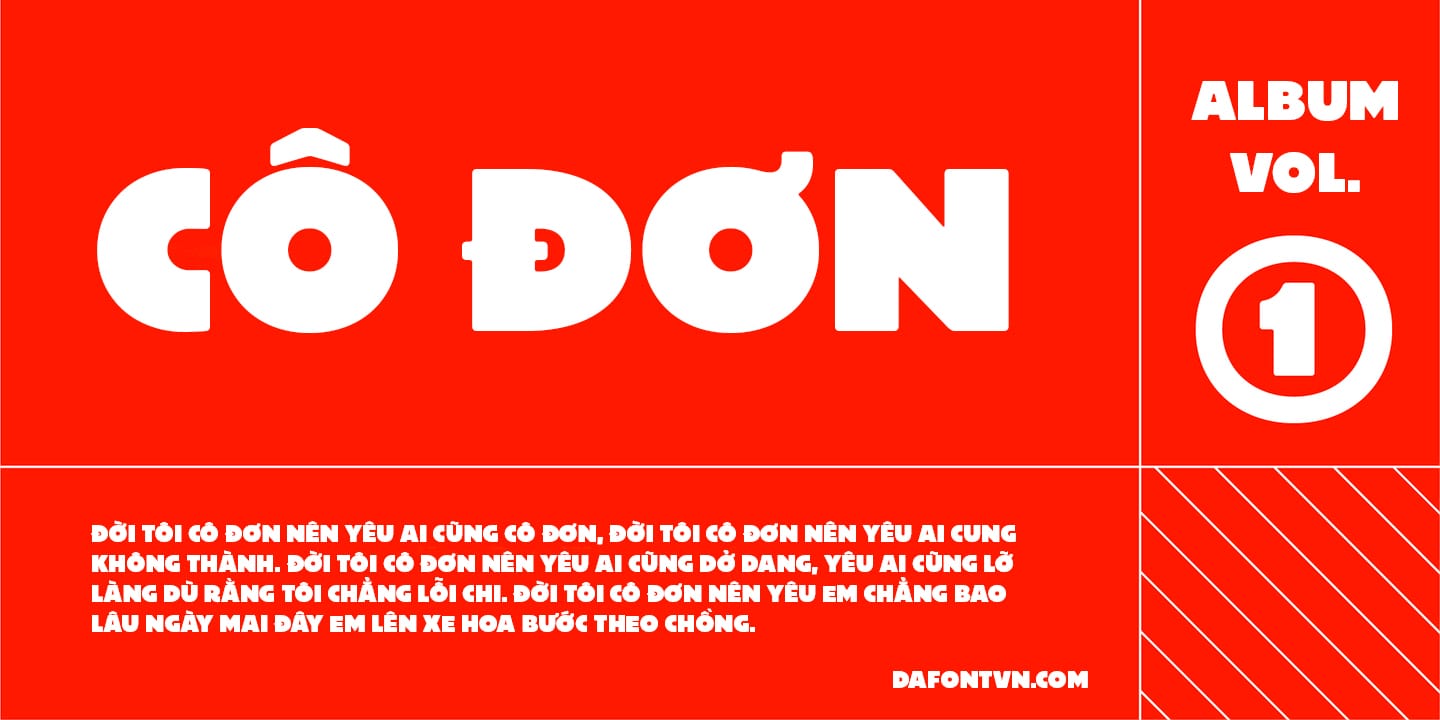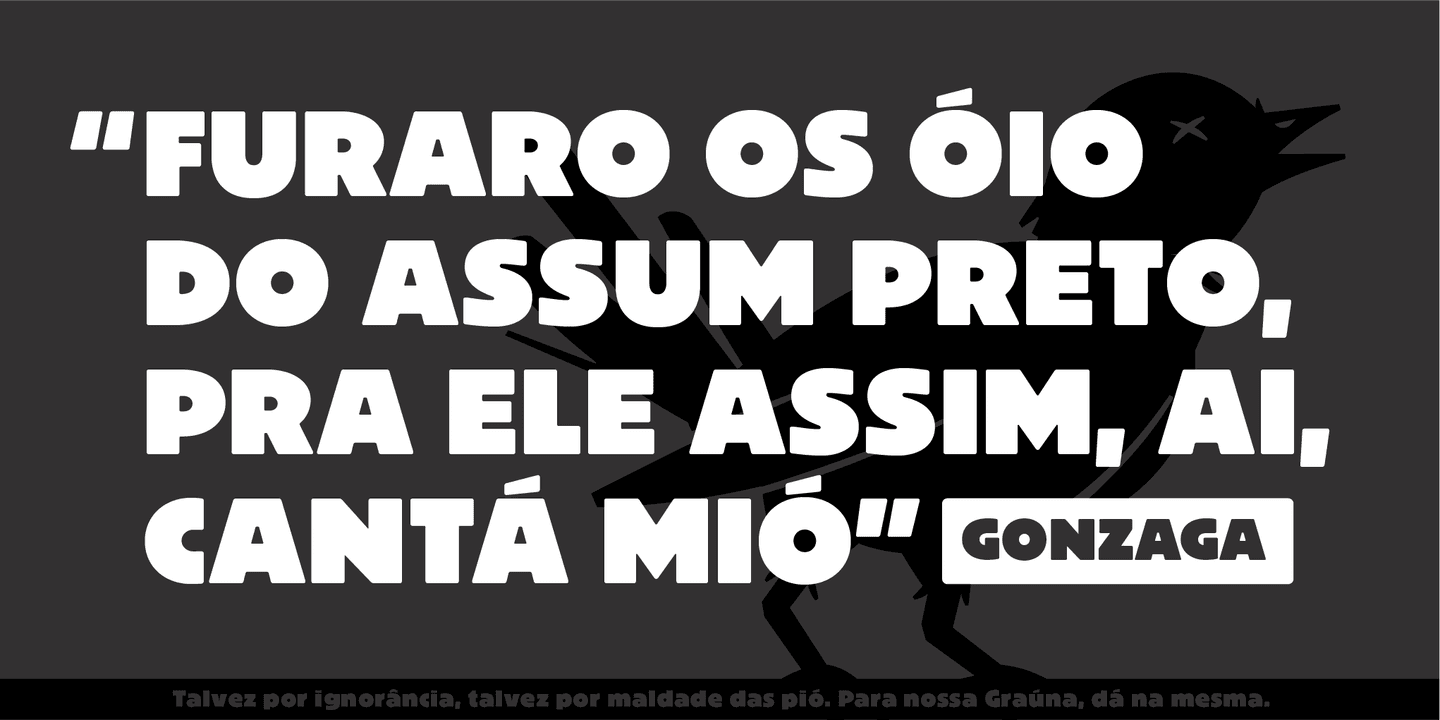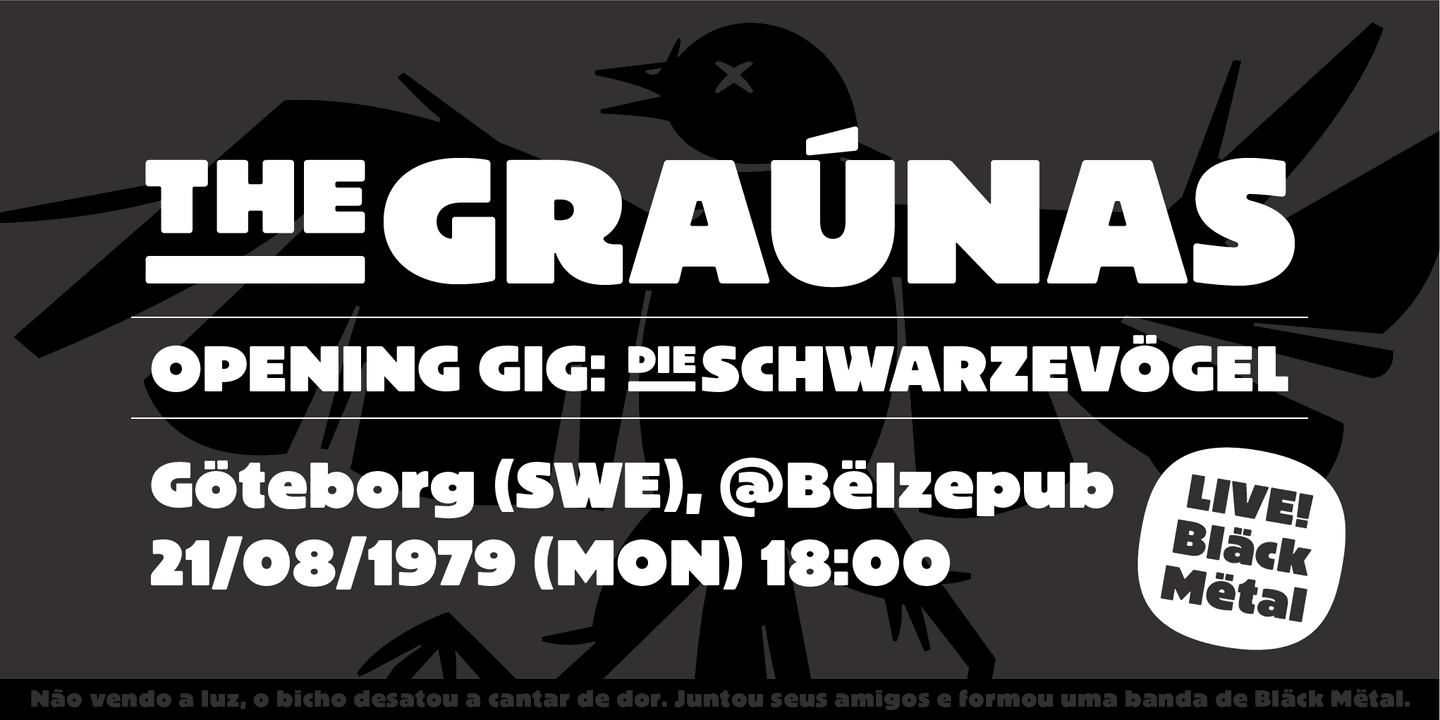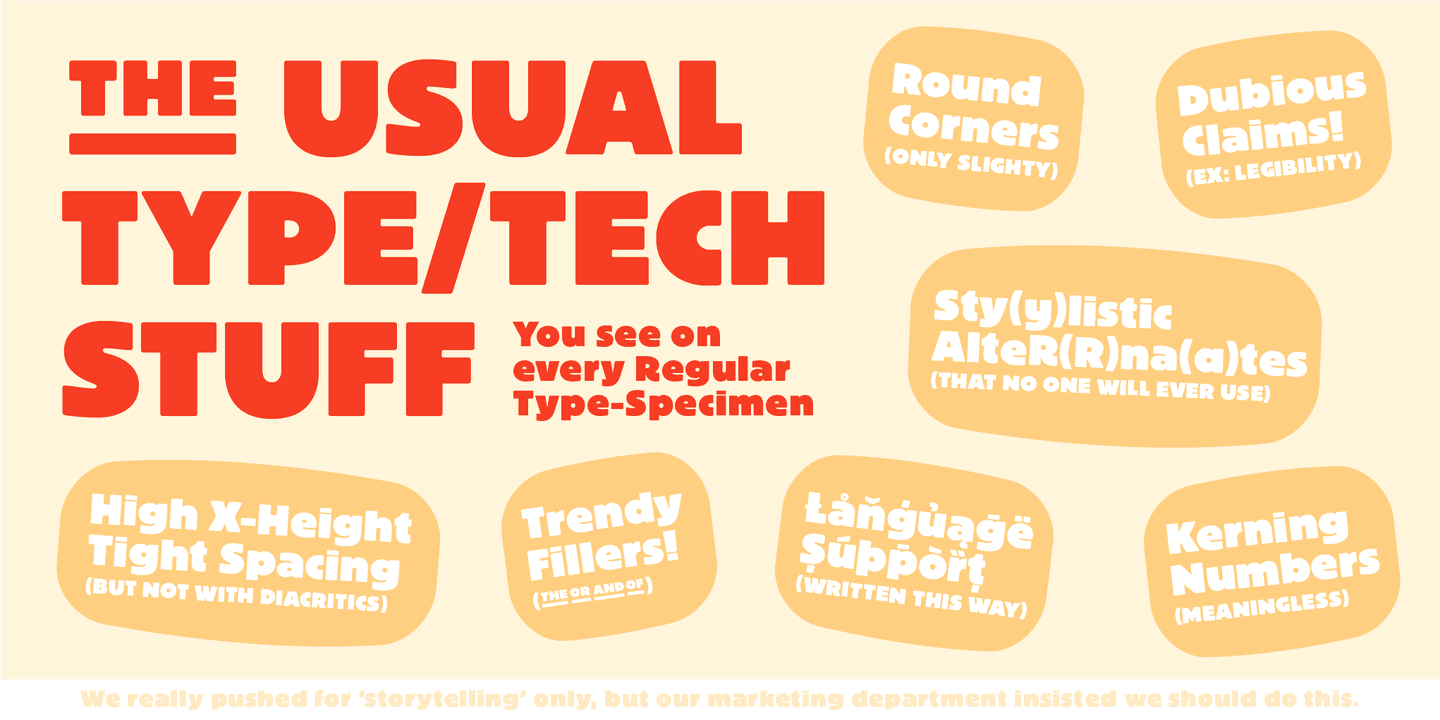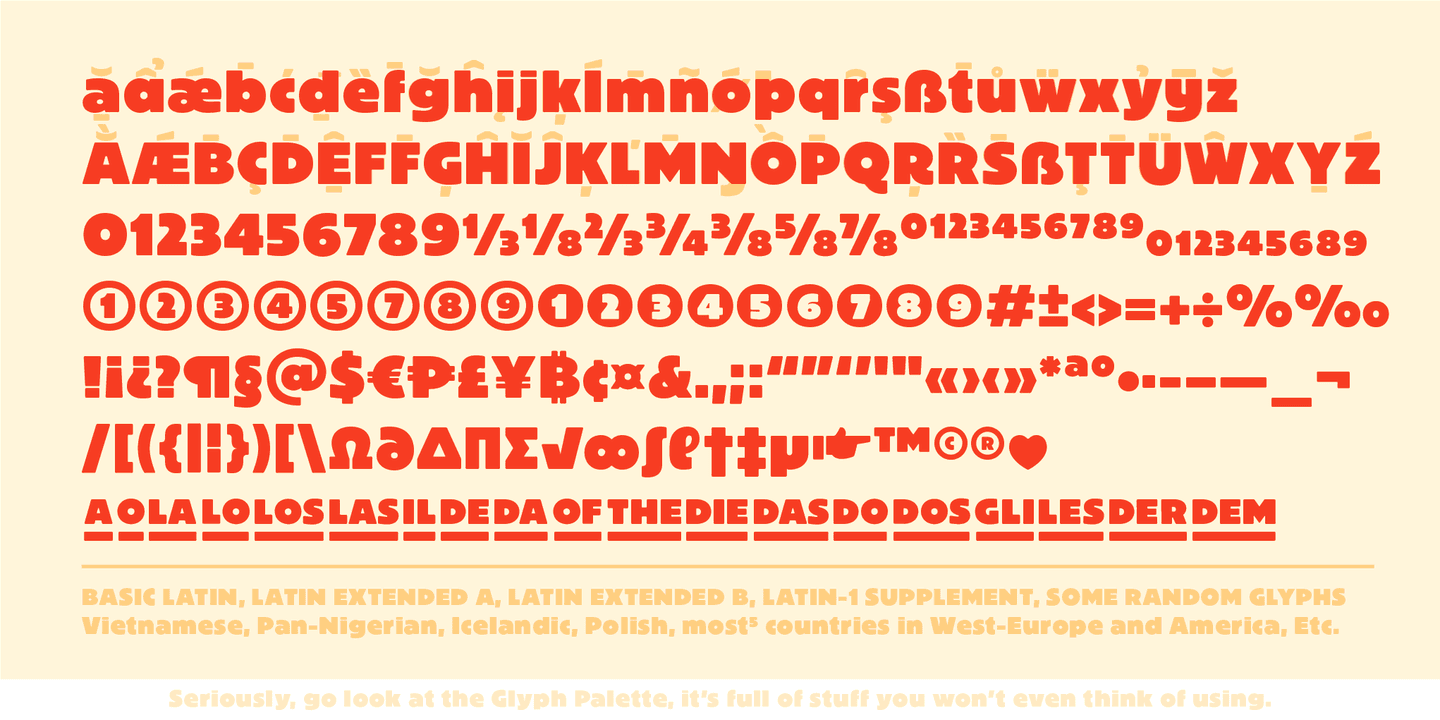
Font Grauna Việt Hóa – Font chữ to, đậm
Grauna Việt Hóa là ‘serious typeface’ đầu tiên của Typeóca. Đây là một font chữ phù hợp dành cho các thiết kế tiêu đề hoặc logo bởi các chữ cái được thiết kế với các nét đậm và to.Ý tưởng là tạo ra một bản phục hồi của Block Heavy, loại bỏ cấu trúc ‘gồ ghề’ từ đường viền của nó. Mặc dù có những bản phục hồi khác tồn tại, hầu hết chúng tiếp cận như một thể thống nhất, bỏ qua những đặc điểm riêng biệt làm cho trọng lượng Heavy trở nên độc đáo. Tuy nhiên, ở giai đoạn đầu của quá trình phát triển, chúng tôi nhận ra rằng nhiều điều kỳ lạ của nó chỉ có thể xảy ra chính xác vì ‘cấu trúc gồ ghề’ chúng tôi đang cố gắng loại bỏ. Như vậy, chúng tôi bắt đầu đi xa và xa hơn so với mô hình ban đầu, và suy nghĩ về kiểu chữ theo cách riêng của nó, tạo ra một kiểu chữ sans serif ấn tượng nhưng thân thiện, lý tưởng cho logo và tiêu đề ngắn.